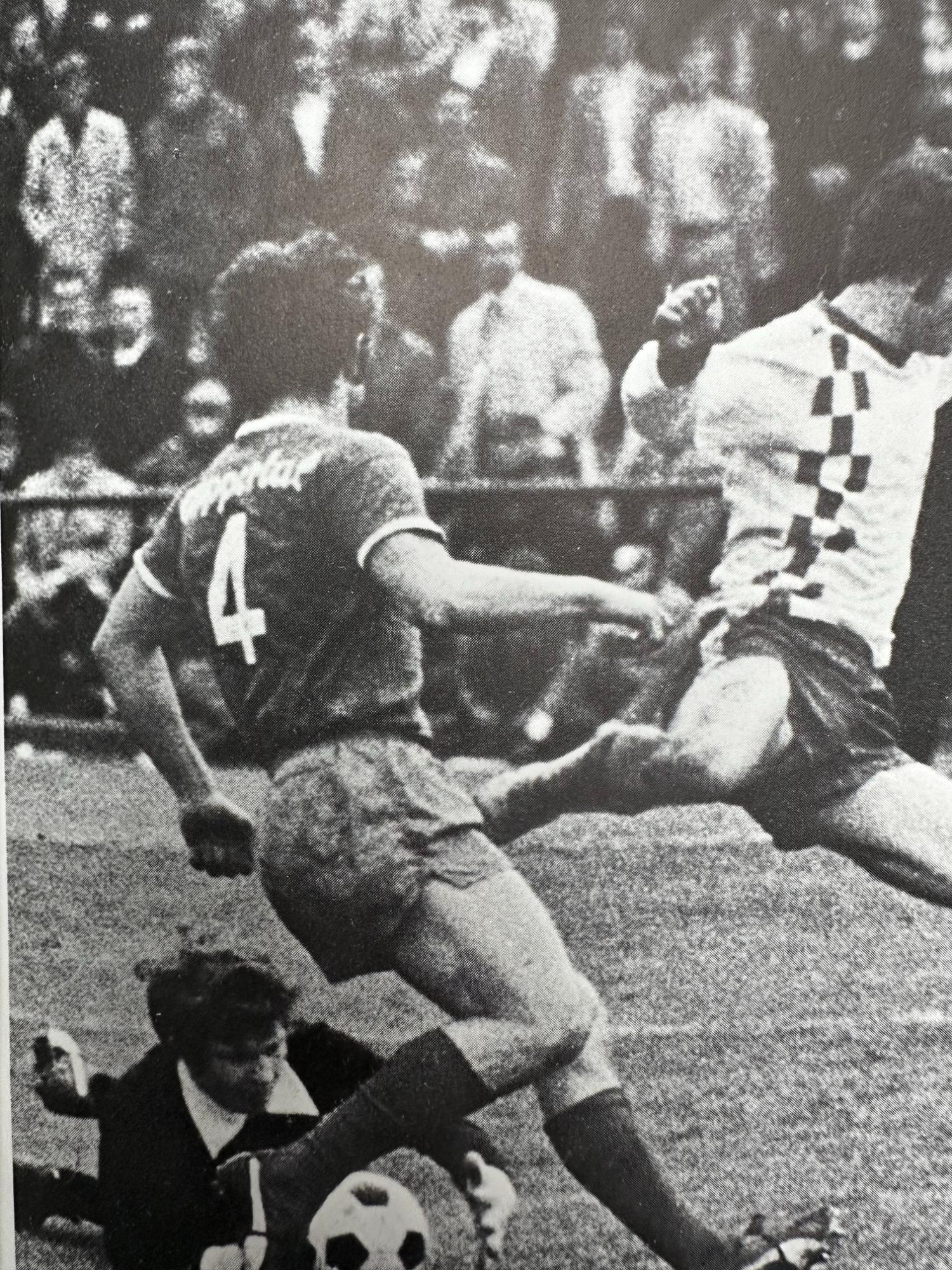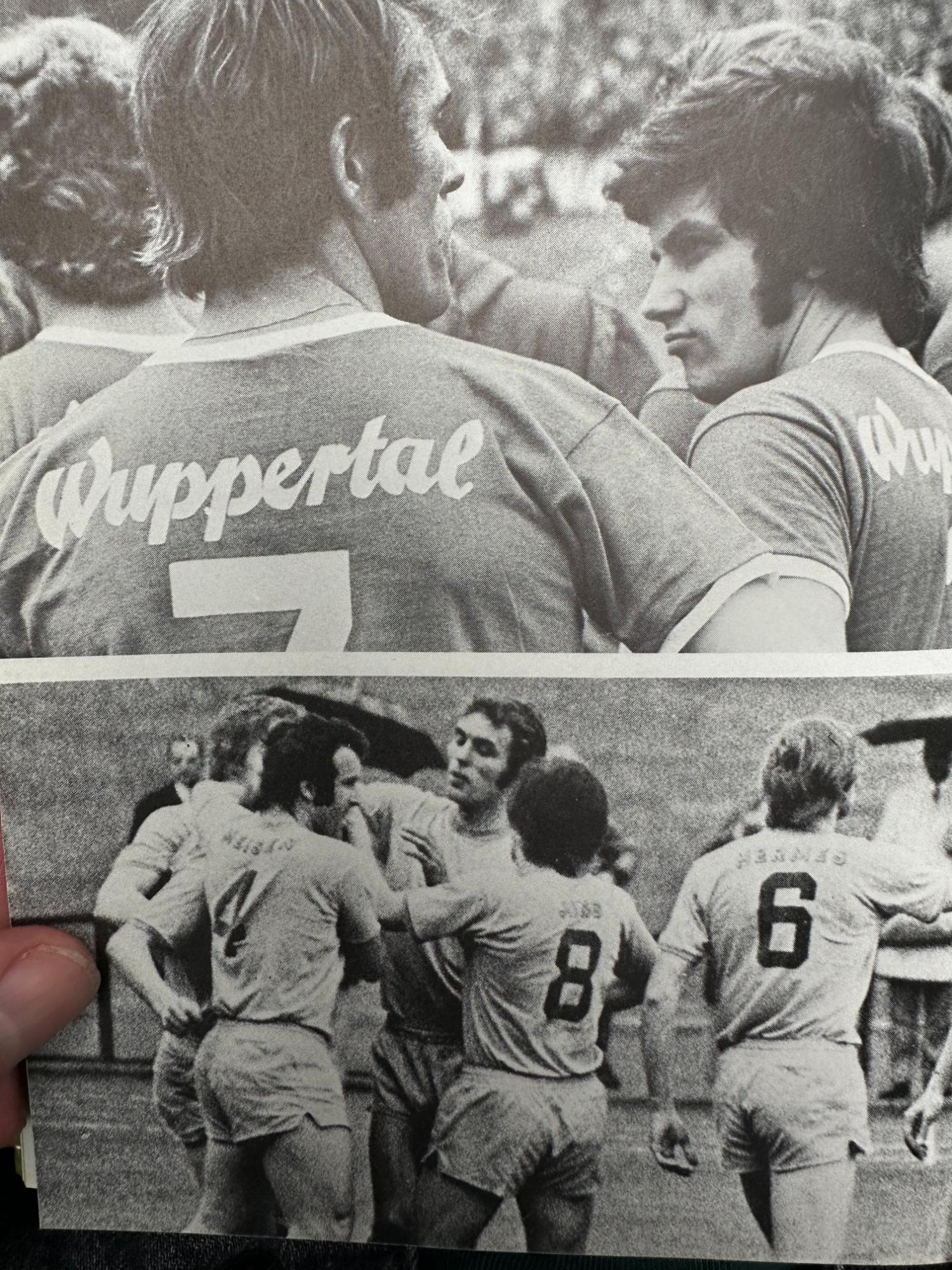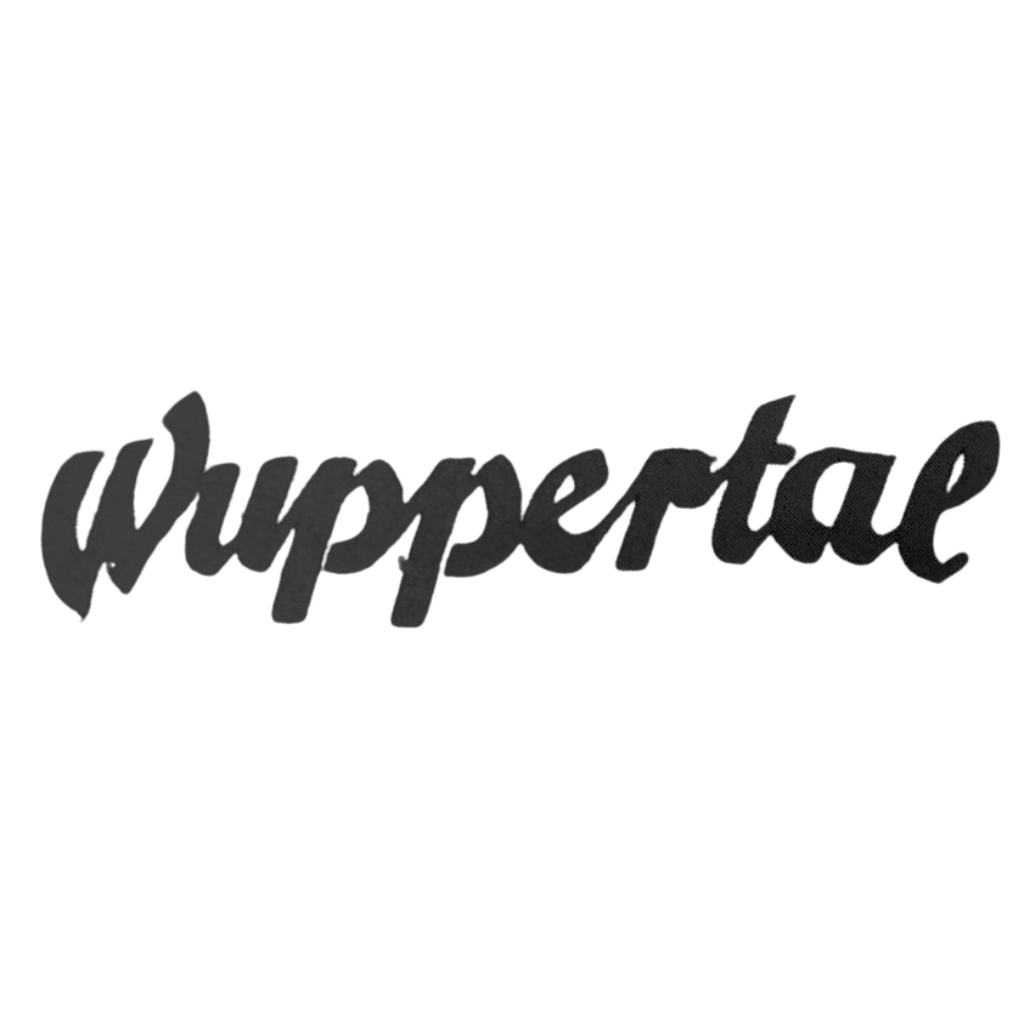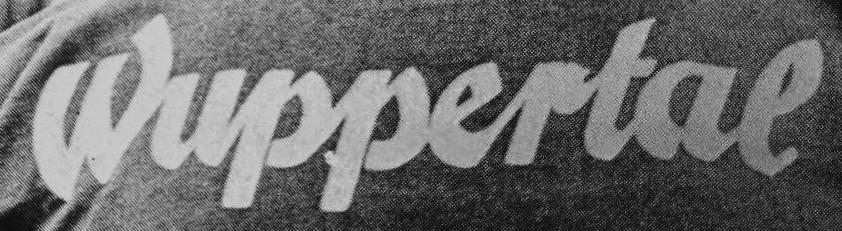
Suche charakteristische, gebrochene Schrift von einem Wuppertal-Trikot aus dem 70ern
ich suche diese oder eine möglichst ähnliche Schrift, die der Wuppertaler SV in den 70er Jahren auf dem Trikot trug. Besonders markant sind hier das W und das l. Das Bild stammt aus dem Buch 'WSV vor… noch ein Tor!' aus dem Wolfgang Schwarze Verlag aus dem Jahr 1972. Leider finde ich keine weiteren Referenzen online.
Ich suche diesen, oder einen sehr ähnlichen Font, der auch was kosten darf. Das ähnlichste, was ich soweit finden konnte sind Christian Egenolff und die Eckmann-Schrift. Allerdings sind genau das W und das l doch sehr anders.
Das ist ein typisches Beispiel von Lettering. Ein Schriftzug, speziell für diese Anwendung erstellt. Keine Satzschrift wird dem nahe kommen.
Deine genannten Alternativen kommen aus der Zeit des Jugendstils. Besser wäre es, bei den deutschen Schreibschriften aus der Mitte des 20. Jahrhunderts zu bleiben. Schau mal durch diese Liste: